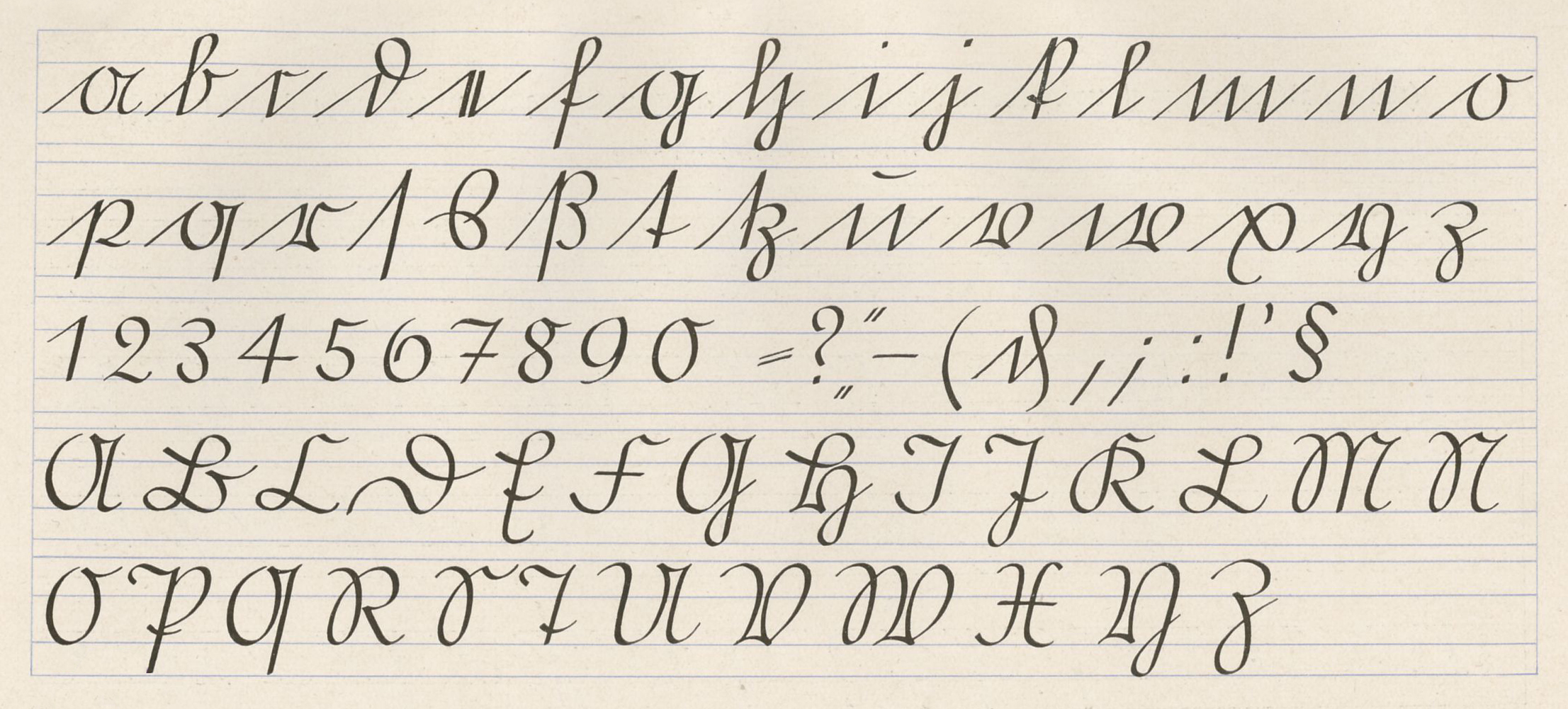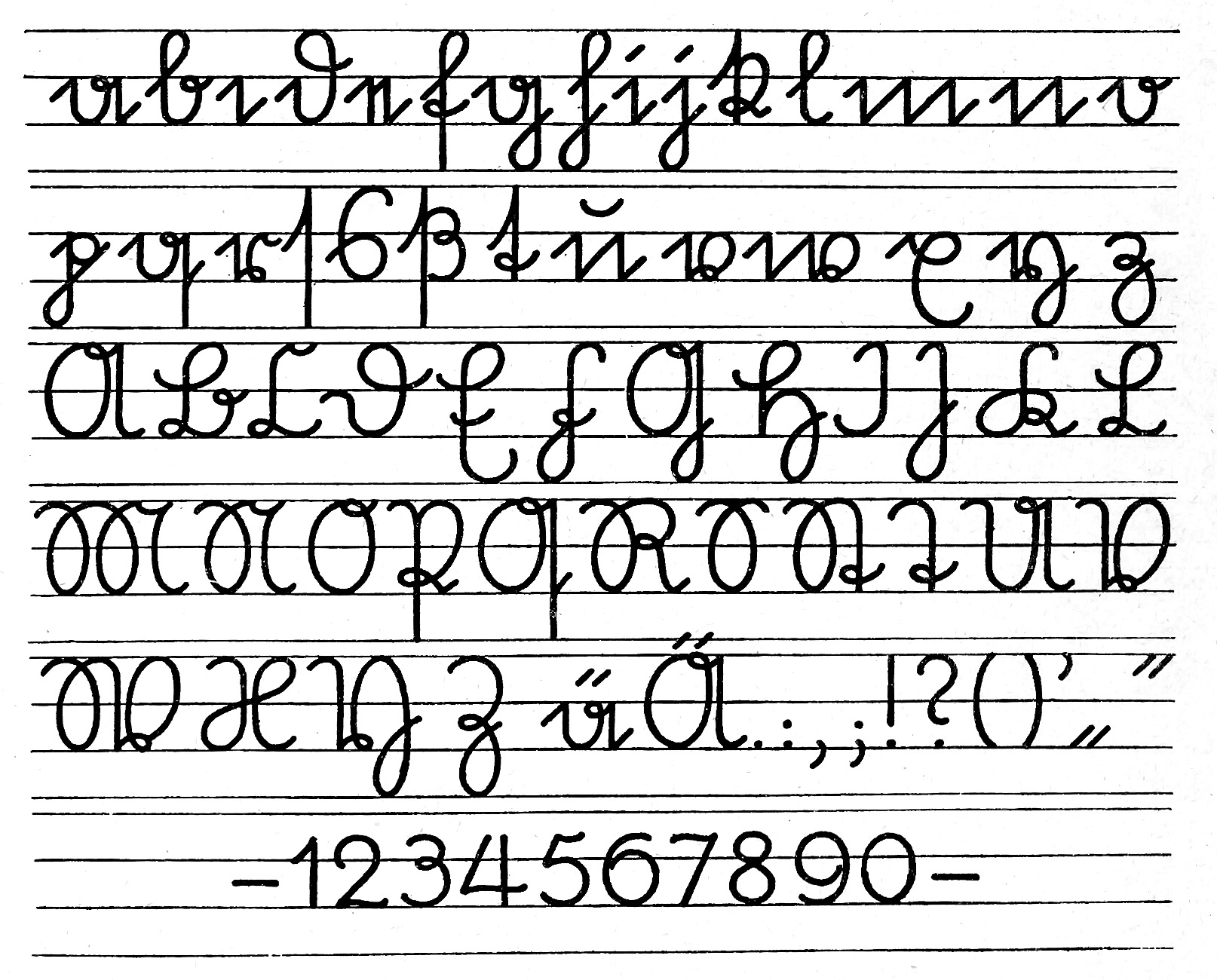
Deutsche Schreibschriften – Von der Kurrent zur Sütterlin
Geschichte und Merkmale der deutschen Schreibschriften: Kurrent, Sütterlin und weitere Formen – und warum sie heute weitgehend verschwunden sind.
Unter dem Begriff deutsche Schreibschriften versteht man jene Schreibhandschriften, die sich im deutschsprachigen Raum über Jahrhunderte entwickelt haben und sich deutlich von den lateinischen Schreibschriften unterscheiden. Die bekanntesten Vertreter sind die deutsche Kurrentschrift und die Sütterlinschrift.
Dieser Artikel gibt einen Überblick über ihre Entstehung, ihre Merkmale und ihren Niedergang.
Die deutsche Kurrentschrift
Die Kurrentschrift (von lateinisch currere = laufen) war über Jahrhunderte die vorherrschende Alltagsschrift im deutschen Sprachraum.
Illustration: Charakteristische Formen der deutschen Kurrentschrift von Andreas Praefke (gemeinfrei)
Entstehung und Verbreitung
Sie entwickelte sich aus spätmittelalterlichen und frühneuzeitlichen Kursiven und wurde ab dem 16./17. Jahrhundert zur Standard-Schreibschrift in Schulen, Verwaltung und privatem Schriftverkehr. Im Gegensatz zur lateinischen Schreibschrift besaß die Kurrent stark vereinfachte, oft spitze und gebrochene Formen.
Typische Merkmale
- Deutliche Ober- und Unterlängen
- Viele Buchstaben wirken eckig oder spitz
- Bestimmte Buchstaben (z. B. e, h, s, x) weichen stark von der lateinischen Form ab
- Die Schrift ist auf schnelles Schreiben mit der Feder ausgelegt
Bis weit ins 20. Jahrhundert hinein konnten die meisten Menschen im deutschsprachigen Raum Kurrent lesen und schreiben.
Die Sütterlinschrift
Anfang des 20. Jahrhunderts galt die Kurrent vielen als unregelmäßig und schwer erlernbar. Der Grafiker und Pädagoge Ludwig Sütterlin (1865–1917) entwickelte deshalb eine reformierte Schreibschrift.
Illustration: Sütterlinschrift – die reformierte deutsche Schulausgangsschrift (gemeinfrei)
Einführung
Die Sütterlinschrift wurde ab 1915 in Preußen als verbindliche Schulausgangsschrift eingeführt und später in weiteren deutschen Ländern übernommen. Sie sollte:
- einheitlicher und klarer sein als die bisherige Kurrent
- für Kinder leichter erlernbar sein
- weiterhin den Charakter einer deutschen Schreibschrift bewahren
Merkmale
Sütterlin wirkt im Vergleich zur älteren Kurrent ruhiger und regelmäßiger. Die Buchstabenformen sind vereinfacht, behalten aber die typischen Merkmale der deutschen Schreibschrift bei. Besonders auffällig sind die Formen von s, h, e und f.
Weitere deutsche Schreibschriften
Neben Kurrent und Sütterlin gab es weitere Ausprägungen:
- Offenbacher Schrift von Rudolf Koch – eine künstlerisch geprägte, ausdrucksstarke Schreibschrift
- Regionale und schulische Varianten der Kurrent
- Gelegentliche Versuche, deutsche und lateinische Elemente zu verbinden
Illustration: Offenbacher Schrift – eine künstlerische deutsche Schreibschrift von Rudolf Koch (gemeinfrei)
Diese Schriften hatten jedoch nie die gleiche Verbreitung wie Kurrent und Sütterlin.
Der Übergang zur lateinischen Schreibschrift
Ab den 1940er-Jahren wurde die deutsche Schreibschrift schrittweise verdrängt.
Illustration: Lateinische Schreibschrift – die nach 1941 durchgesetzte Normalschrift
Wichtige Stationen:
- 1941 verfügte ein Erlass die Einführung der lateinischen Schreibschrift als Normalschrift
- Nach 1945 setzte sich die lateinische Schreibschrift in beiden deutschen Staaten durch
- In den Schulen wurde Sütterlin bzw. Kurrent nach und nach nicht mehr gelehrt
Die Gründe waren sowohl praktische (internationale Lesbarkeit, Vereinfachung) als auch politische. Damit endete eine jahrhundertelange Tradition der deutschen Schreibschrift im Alltag.
Heutige Situation und digitale Wiederbelebung
Heute können die meisten Menschen Kurrent und Sütterlin nicht mehr flüssig lesen. Die Schriften leben vor allem weiter in:
- historischen Dokumenten und Briefen
- genealogischen Forschungen
- künstlerischen und gestalterischen Kontexten
- digitalen Fonts, die Kurrent- oder Sütterlin-Formen nachbilden
Es gibt inzwischen mehrere digitale Interpretationen dieser Schriften. Sie eignen sich jedoch eher für besondere gestalterische Zwecke als für längere Lesetexte, da die Lesbarkeit für Ungeübte gering ist.
Fazit
Die deutschen Schreibschriften – allen voran Kurrent und Sütterlin – bilden ein eigenständiges Kapitel der Schriftgeschichte. Sie waren über lange Zeit das selbstverständliche Medium der handschriftlichen Kommunikation im deutschen Sprachraum und wurden erst im 20. Jahrhundert von der lateinischen Schreibschrift abgelöst.
Wer alte Briefe, Tagebücher oder Urkunden lesen möchte, kommt an diesen Schriften nicht vorbei. Für die typografische Praxis der Gegenwart spielen sie vor allem als historisches und gestalterisches Phänomen eine Rolle.